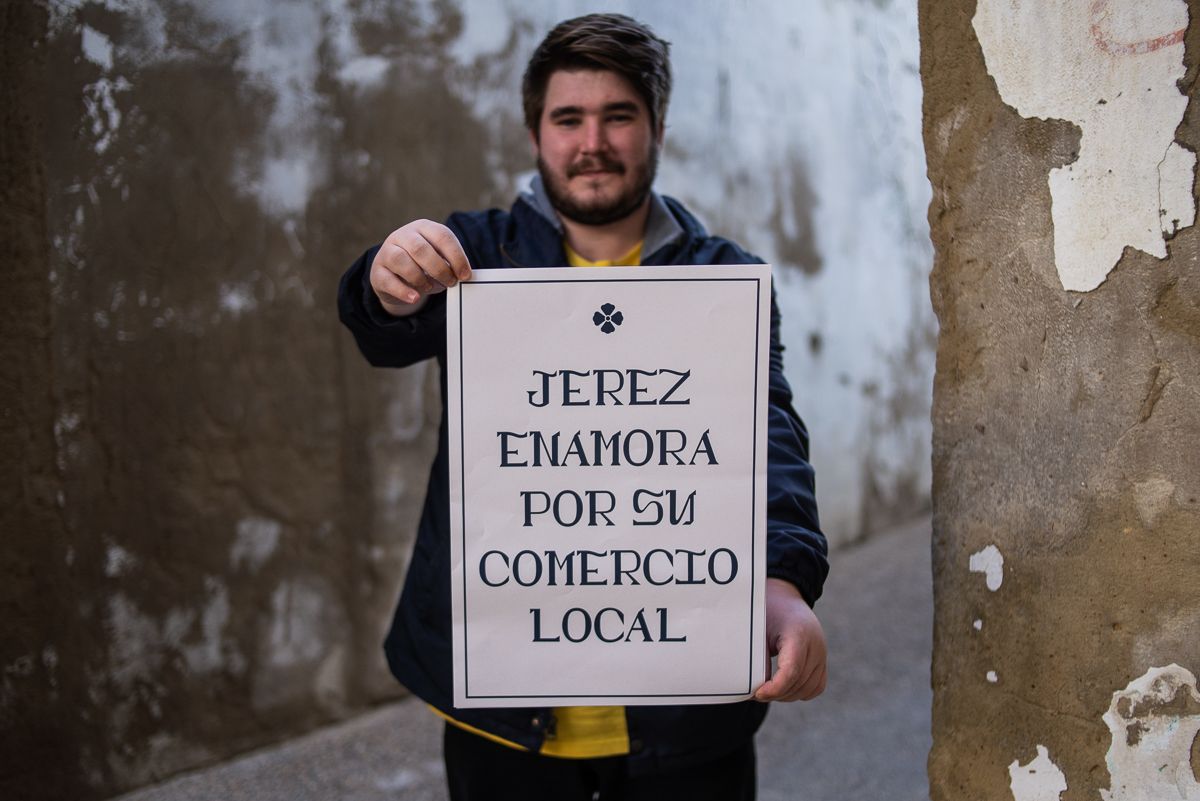
Enrique Guillén Domínguez es un joven jerezano de 24 años que siempre ha estado ligado al mundo de la creatividad y la imagen. Desde pequeño, confiesa, le obsesionan los símbolos, el grafismo, la comunicación... la historia y la cultura, en general. Siguiendo su vocación, marchó hace unos años a Madrid, al IED (Instituto Europeo de Diseño), para estudiar diseño gráfico. Como trabajo de fin de grado (TFG), tras mucho diagnóstico e investigación, publicó Asta, proyecto de creación de una tipografía que funciona como señalética e identidad para su ciudad natal.
Pese a que siete de cada diez vías del centro histórico de Jerez, según él mismo ha documentado, su iniciativa ha sido recibida con tibieza en su tierra. Y eso que dicho proyecto fue premiado en septiembre del pasado año en los prestigiosos ADG Laus 2020 como uno de los trabajos fin de estudios de excelencia en el paranoama nacional. A Enrique le apena haber obtenido esa repercusión fuera de casa y el silencio dentro, pero no desfallece y lo seguirá intentando. Sabe que en Jerez, políticos al margen, hay una ola creciente de concienciación ciudadana sobre los temas patrimoniales, sobre la necesidad de recuperar el Jerez olvido, y, por eso, quizás sea cuestión de tiempo que Asta se materialice como una propuesta para "hacer comunidad" y crear "sentimiento de pertenencia".
"Siempre tuve claro que me quería dedicar al tema gráfico, a crear imagen, desde pequeño ha estado ahí. Fue positivo tenerlo claro, era vocacional", cuenta a lavozdelsur.es el joven creativo jerezano, que pese a su corta trayectoria ya ha teletrabajado en una agencia de diseño en Barcelona y ha desarrollado la identidad del restaurante Tohqa en El Puerto, un referente de la mano del cocinero Edu Pérez que ya ha sabido conquistar los paladares de algunos de los mejores chefs del país. Jerez enamora por su comercio local es otro de los carteles que ha diseñado Guillén y que están escritos con su tipo, la Asta jerezana. Probablemente lo hayan visto en algunas puertas de entrada a comercios del centro.
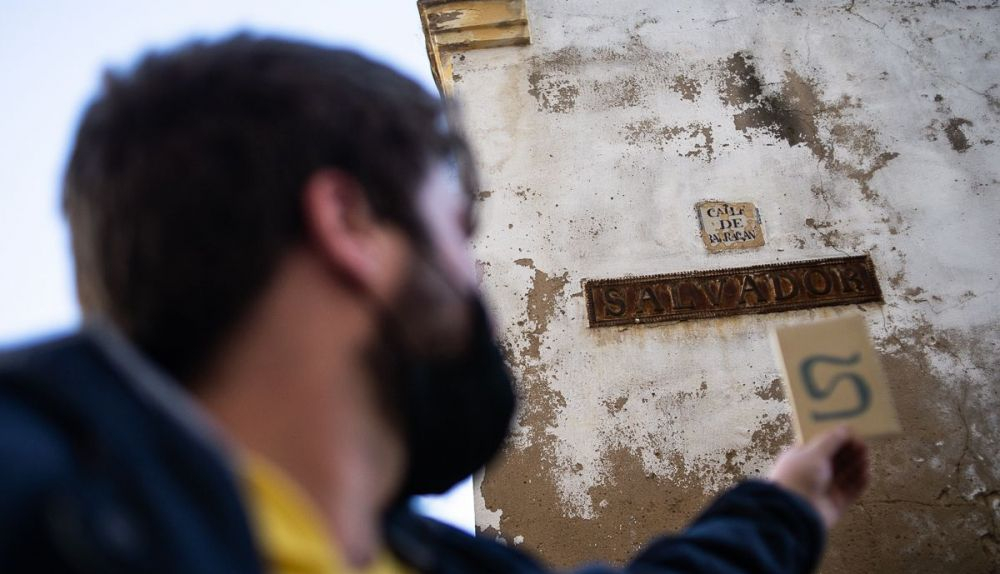
"Al final —abunda el diseñador—, esta tipo es una mezcla de todo el patrimonio gráfico que hemos podido tener en siglos de historia: desde el origen primitivo de la tipografía, que está en las lápidas funerarias que estaban en Mesas de Asta, hasta la mezcla de todo el universo visual que hemos tenido con la industria del vino. Y también meter los rótulos de los comercios clásicos, los de Olavide cuadrados del siglo XVIII, y los propios luminosos de las bodegas… Mezclar toda es gráfica para conseguir un elemento nuevo que ha sido esta tipografía, con un trocito de toda la historia de Jerez".
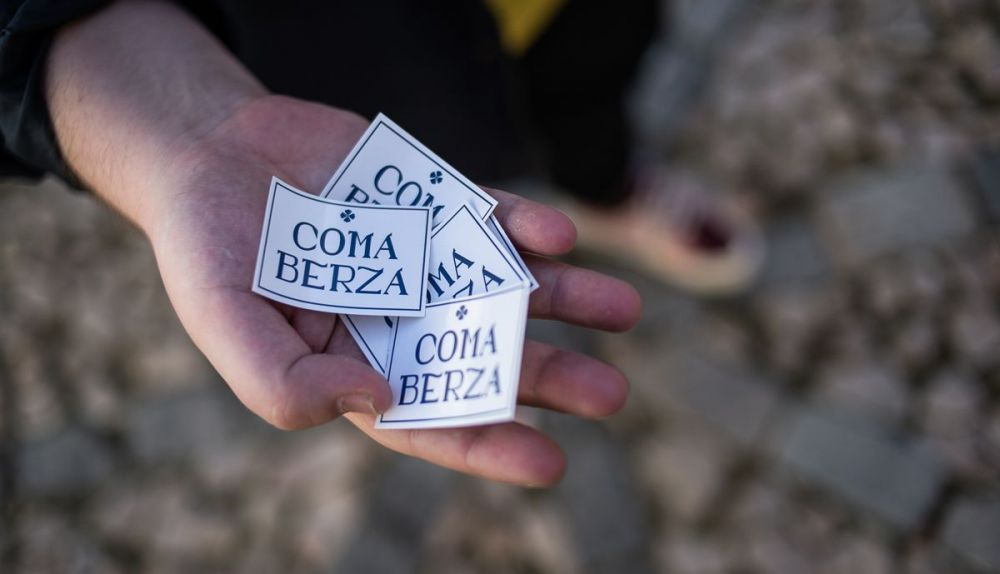
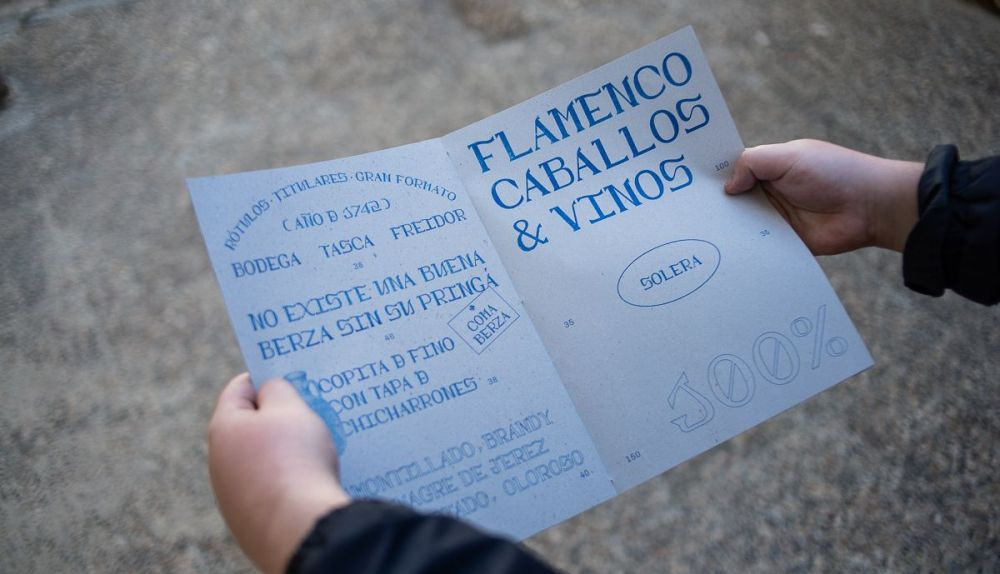
Basada en las inscripciones antiguas encontradas por la zona, se ha desarrollado una tipografía decorativa y mono espaciada, que responde a las necesidades gráficas de la ciudad y al imaginario colectivo. El proyecto está compuesto por una versión digital y una versión impresa en cerámica, que funcione para rótulos y señalética callejera.
"Asta es identidad tanto para la gente de dentro como para la que viene de fuera. En muchas ciudades se opta por este tipo de elemento gráfico unitario, y se han dado cuenta de que aportan mucha identidad y les definen. Es un proyecto con mucha carga patrimonial, simbólica, un universo muy completo… y que también quiere dar voz a algo que se está abandonando porque casi el 70% de los rótulos de las calles del centro están abandonados… Menos mal que existe Google Maps, pero si llega cualquiera de fuera, o incluso de aquí, puede perderse hasta por las calles sin nombre. Otras ciudades potencian ese patrimonio gráfico y nosotros lo tenemos descuidado", defiende. Y añade: "A largo plazo, lo ideal sería poner esto en práctica. Cuando me puse a investigar tuve en cuenta todo, incluyendo que el usuario final que consuma esa tipografía , el jerezano, la sienta como suya, que sea funcional".
Como muchos jóvenes, "sigo buscando mi hueco", sin parar de desarrollar proyectos y "ayudando a la peña": "No me quejo, no solo soy yo el que está jodido, hay mucha gente igual y, aun así, siguen trabajando y generando proyectos". Tras contactar con la plataforma por la puesta en valor del yacimiento de Asta Regia, Enrique Guillén es consciente de que su propia iniciativa "encaja con el momento de mayor sensibilidad patrimonial en la ciudad de los últimos tiempos". Lo que no está tan claro es que encaje con la sensibilidad de quienes deciden en última instancia, que son los políticos.
"El proyecto espero que sirva para reivindicar y, a día de hoy, en Jerez desde luego están valorándose este tipo de cosas. Si se puede por mi parte aportar el granito de arena, yo encantado. Esto está pensado para utilizarlo todos y que sirva para comunicarnos y reivindicar las cosas que nos faltan, que se da mucha importancia a cosas superficiales y olvidamos de revalorizar lo que tenemos".
¿Cada azulejo una letra? ¿Una unidad tipográfica para al menos todas las calles del centro? Eso queda abierto... "Quiero recalcar que Asta es un elemento bastante versátil, amplio, y se puede utilizar esta tipo como se quiera, no solo está pensado para la propuesta de calles, sino que también lo que quiero es que se busquen otros soportes, como representación gráfica del nombre de Jerez". La simbología y el poder de la tipografía como identidad de las ciudades es algo que se viene trabajando desde hace décadas. Iamsterdam es una presentación, un eslogan y también un ícono físico, pero también es el lema colectivo de la capital de los Países Bajos y sus residentes. A finales de los 70, fue la ciudad de Nueva York la que, sumida en una grave depresión y un índice de criminalidad desolador, encargó a Milton Glaser una campaña para revalorizar la Gran Manzana. Y así surgió I love New York. Una idea que estaba prevista que durase un par de meses y que, tipografía incluida, se ha acabado convirtiendo un icono de la identidad de los neoyorquinos de dentro y de fuera.
Con esos ejemplos, no parece que lo de Asta sea descabellado. "Estoy bastante contento porque el proyecto tuvo reconocimiento a nivel nacional, pero al mismo tiempo ando un poco desganado porque aquí en Jerez no se le haya prestado mucha atención. Tener un Laus fue bastante guay por tener repercusión a nivel nacional, pero es un poco frustrante que aquí en casa no haya habido interés".